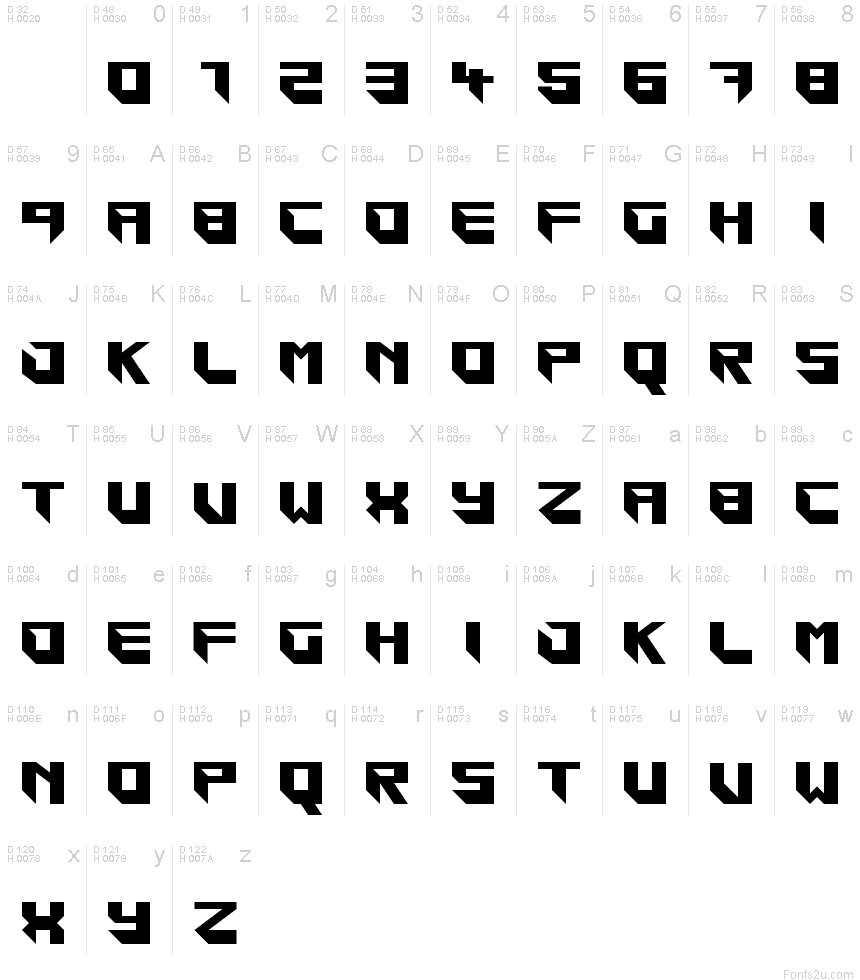
Blockar 字体
Blockar
Philipp Hubert
由 Philipp Hubert 设计的 Blockar 是一款免费的几何 techno 展示字体,由宽阔的方形结构和犀利的对角切割构成。它的字母类似于模块化面板,带有狭窄的矩形开口和呈明显角度切割的转角。整体轮廓厚重且具有机械感。
它能够将标题转化为类似界面的图形,适用于游戏封面、电子音乐艺术作品以及科幻海报。重复出现的切口和硬朗的连接处也非常适合科技品牌的设计,其中的字形可以让人联想到电路、机械或有棱角的屏幕图标。